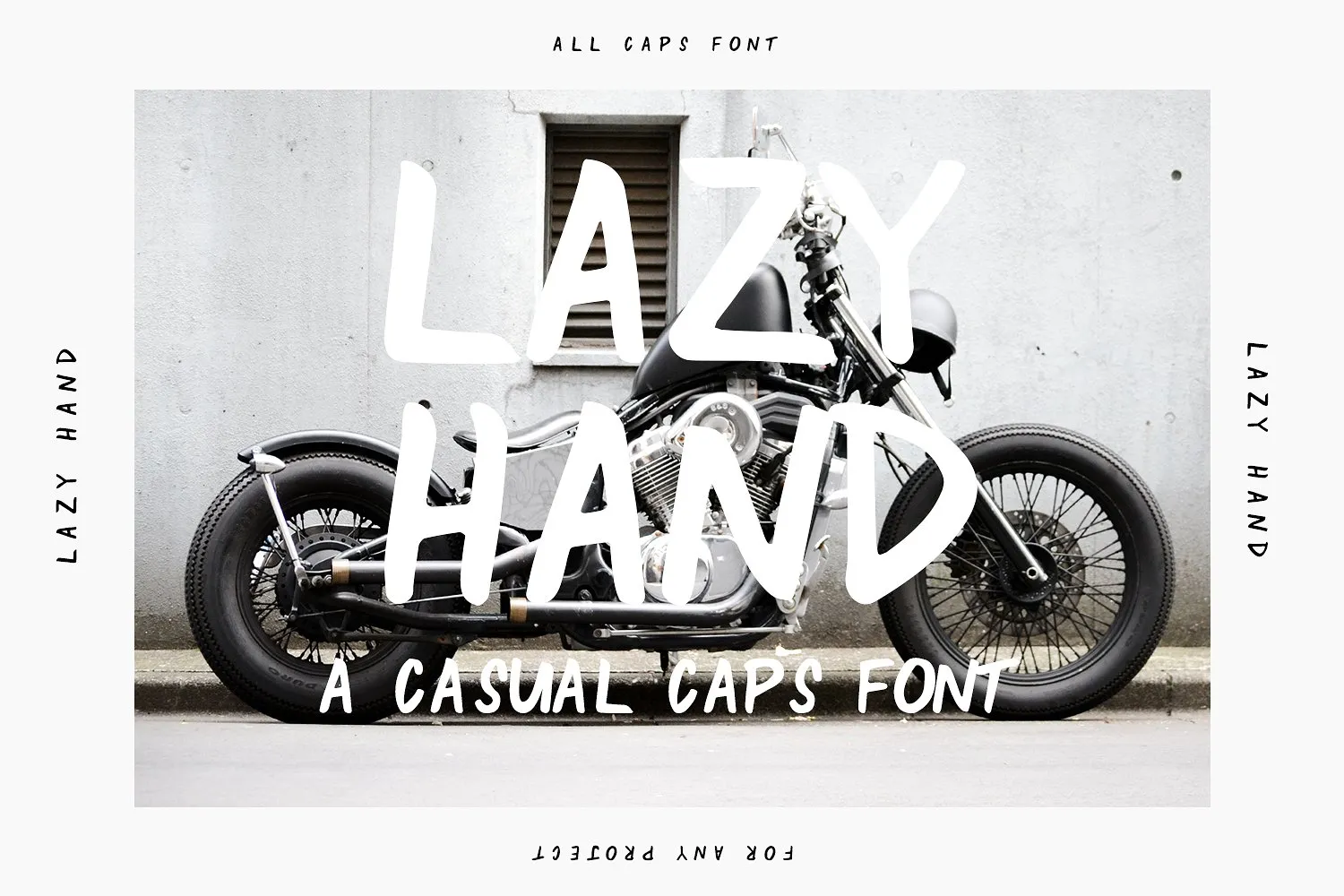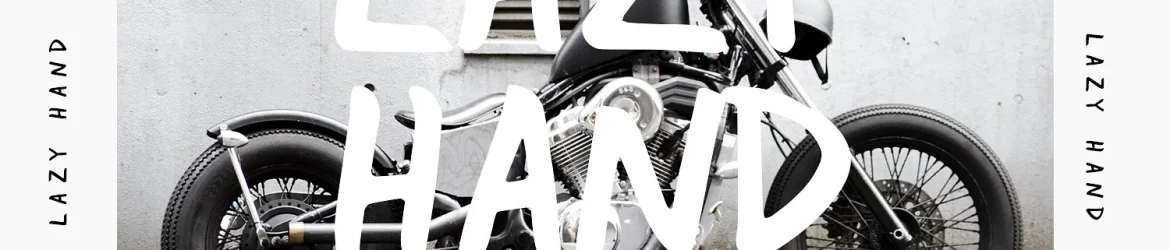
Descubra a tranquilidade no design com Lazy Hand Font! Desenhada por Jenna Maxfield, esta é uma fonte premium disponível na CreativeMarket. Agora, em uma gentil oferta, ela está gratuita para download hoje. Lazy Hand é um font casual e sólido, ideal para projetos que exigem um toque de relaxamento. Seu estilo handwritten, leve e descontraído, permite que você use esta fonte tanto no formato formal quanto no informal. Seja para criar cartazes, anúncios ou até mesmo artesanato, Lazy Hand oferece inúmeras possibilidades criativas. E com apenas um clique, você pode adicionar uma nota de calma ao seu design — um toque único que o torna único. Que tal experimentar a essência do desenho livre em sua próxima criação?